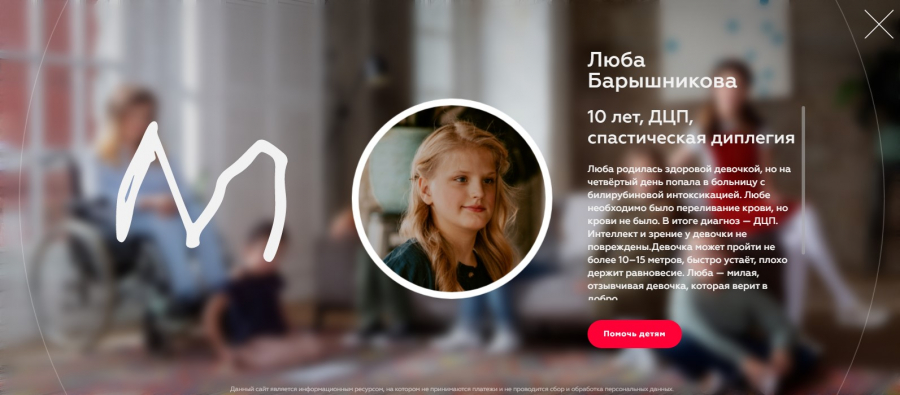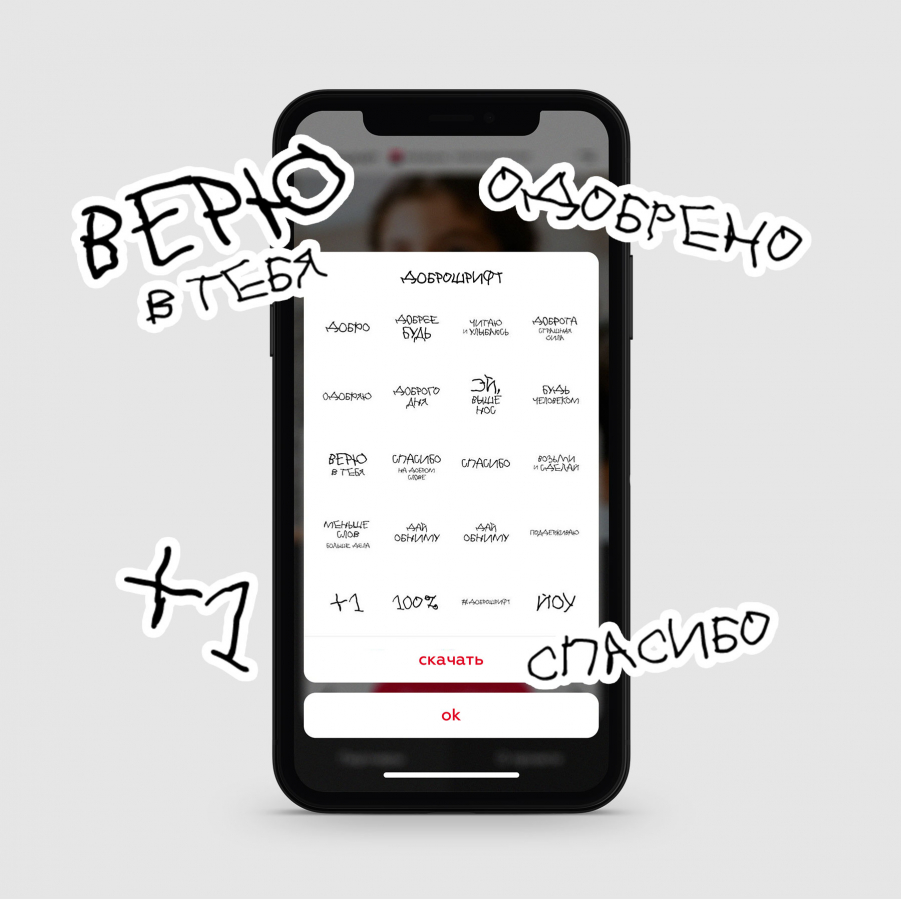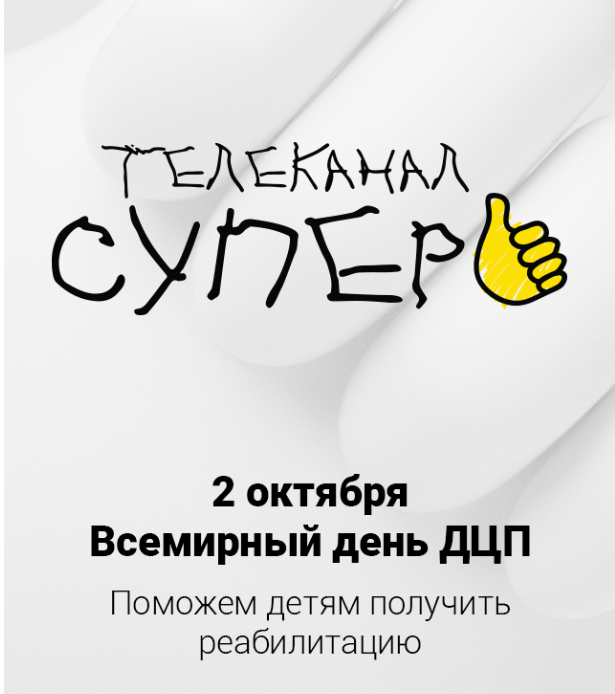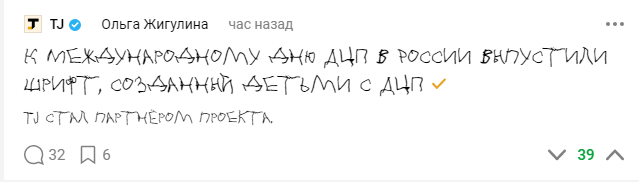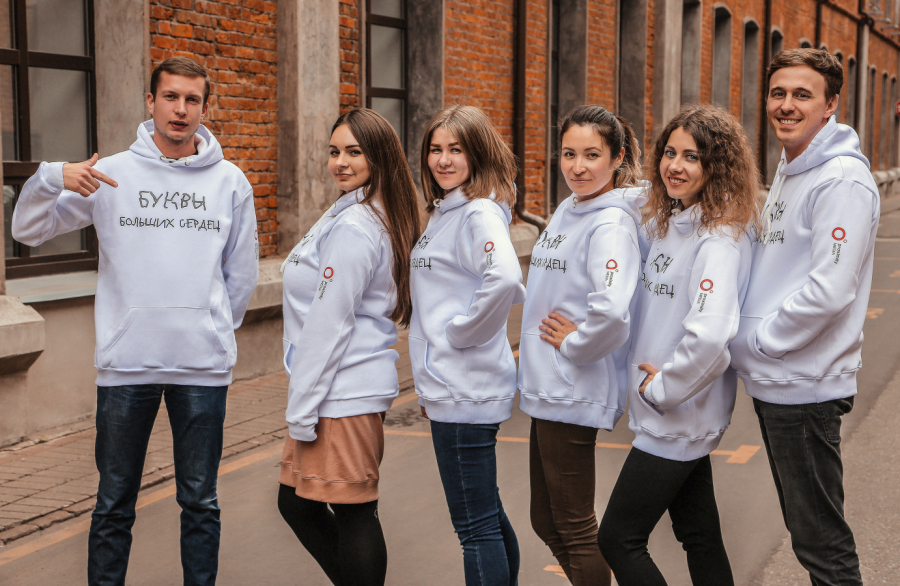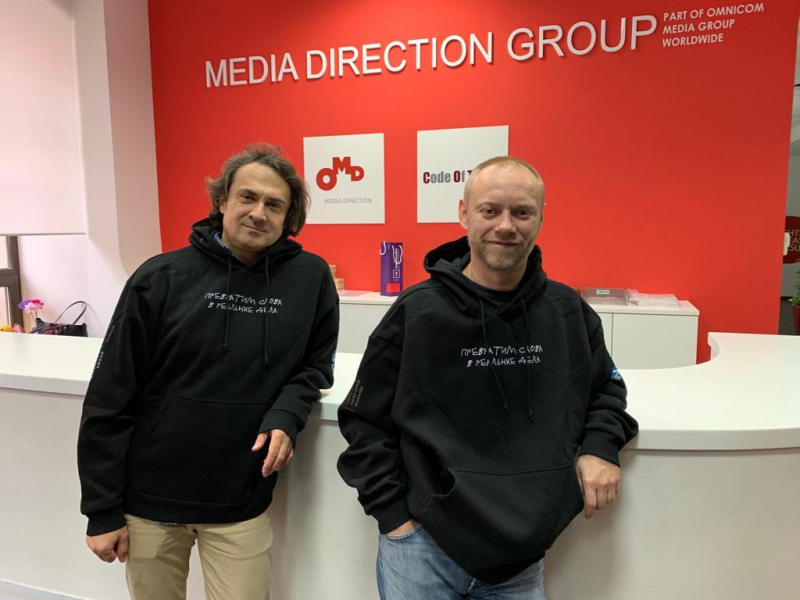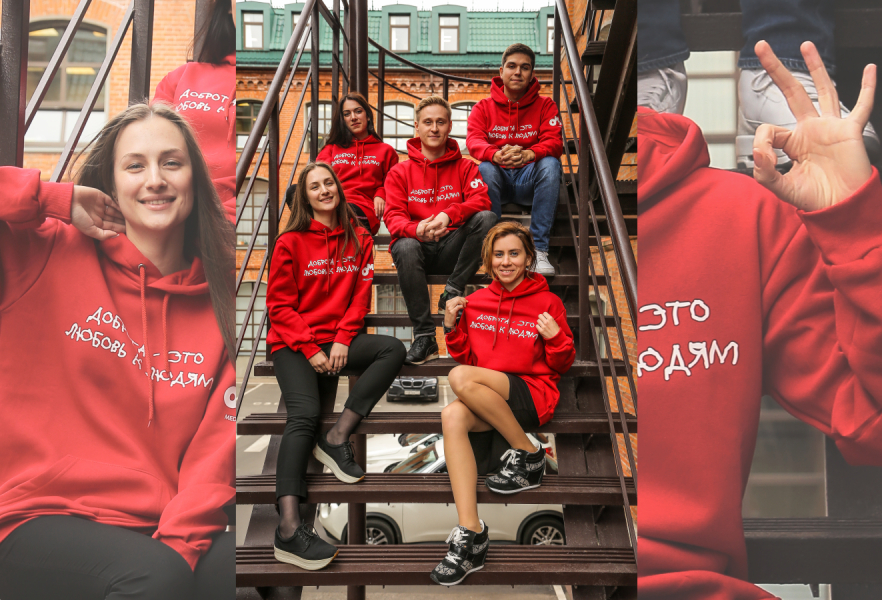
Рекламные группы заменили шрифты в своих соцсетях в рамках социальной кампании ко дню ДЦП
«Доброшрифт» создали дети с ДЦП
«Росбанк» совместно с благотворительным фондом «Подарок Ангелу» и креативным агентством Smetana помог детям с ДЦП создать особый шрифт, получивший название «Доброшрифт». «Доброшрифт» — это средство визуального выражения помощи и поддержки детей с ДЦП.
Согласно концепции, «Доброшрифт» должен заменить привычные нам шрифты — в логотипах, в рекламе, в коммуникациях и продуктах. Команда проекта верит, что дети с ДЦП могут творить несмотря на то, что каждая буква дается им с трудом.
Идею «Доброшрифта» уже поддержали агентства холдинга MEDIA DIRECTION GROUP , перечислив средства в фонд, также к акции присоединились e:mg , Instinct (BBDO Russia Group), заменив корпоративные шрифты в своих соцсетях на «Доброшрифт», а популярные бренды, медиаплощадки и блогеры стали амбассадорами проекта.
Sostav также присоединился к социальной акции и переписал свой логотип «Доброшрифтом».
На специальном сайте кампании можно прочитать истории детей, создавших базовые символы шрифта, скачать Доброшрифт, купить товары с Доброшрифтом и сделать пожертвование, которое пойдет на реабилитацию детей с ДЦП.
Для рекламной индустрии социальная повестка является актуальной и приоритетной.
Создавая ежегодно сотни социально ориентированных проектов в России и в мире, агентства транслируют и популяризуют ценности ответственных брендов, способствуя вовлечению все большего количества людей в решение таких остросоциальных вопросов, как помощь нуждающимся, благотворительность, защита окружающей среды, неравенство полов, эксплуатация детского труда и другие.
Елена Кожадей, директор департамента коммуникаций и рекламы Росбанка:
Росбанк как социально ответственный финансовый институт прилагает много усилий для того, чтобы поддерживать тех, кто в этом действительно нуждается. Мы считаем, что популяризация такого креативного инструмента, как особый шрифт, созданный детьми с детским церебральным параличом, поможет привлечь внимание общественности и вдохновит широкую аудиторию помогать детям с ДЦП.
Андрей Брайович, генеральный директор MEDIA DIRECTION GROUP :
Мы все понимаем, что благотворительность и социальная ответственность — это признак эволюционного взросления общества и бизнеса.
Но также важно понимать, что «бизнес» — это не абстрактная «корпорация», это люди. И все начинается с конкретных людей, которые принимают решение помогать. Спасибо фонду «Подарок ангелу» и нашему партнеру РОСБАНК за возможность стать такими людьми. И отдельное спасибо ребятам, которые потрудились над буквами «Доброшрифта». Это подарок нам всем, напоминающий, что нет ничего невозможного!
Татьяна Тармогина, управляющий директор e:mg :
Мы не раздумывая дали согласие на поддержку данного проекта. Социальная ответственность — большая и сознательная часть корпоративной философии e:mg. Мы рады быть частью социально активного сообщества и вместе с коллегами и индустрией менять мир к лучшему. Призываем всех не оставаться равнодушными и присоединиться к акции «Доброшрифт».
Юлия Губина, генеральный директор агентства Instinct :
Нам очень понравилась идея мы с радостью присоединяемся к акции, чтобы помочь привлечь внимание к проблеме как можно большее количество людей.
Николай Муравьев, генеральный директор Media Wise :
Когда мы видим что-то, что вызывает печаль, сочувствие — нам хочется закрыть глаза, такова природа человека. Поэтому так важны те, кто помогают нам держать глаза открытыми. Распространение информации о проблеме ДЦП — через соцсети, например — это важнейший инструмент благотворительности. Мы также помогли масштабированию акции, разместив за своей счет в Москве часть кампании «Доброшрифт» в ООН.
Я хочу сказать большое спасибо тем организациям, в частности, РОСБАНКу, которые делают так, чтобы как можно больше людей узнали о способах помочь детям. Мы многое можем сделать, когда не закрываем глаза на проблемы и объединяемся вместе.
Акцию поддержало множество рекламистов, маркетологов и медиаплощадок. Среди них Sports.ru, TJ, «Яндекс», Mail.ru Group и другие.
Состав творческой группы:
Благотворительный фонд «Подарок Ангелу» (клиент)
Анастасия Приказчикова — Генеральный директор
Евгения Серикова — Руководитель проектов
Евгения Белотелова- Директор по развитию
Эльвира Балоянц — Координатор по работе с семьями
Михаил Гинзбург — Руководитель отдела по работе с партнёрами
Росбанк (General Partner)
Елена Кожадей — Директор департамента коммуникаций и рекламы
Анастасия Жилина — Начальник отдела рекламы
Андрей Белов — Начальник управления бренда и рекламы SG Russia